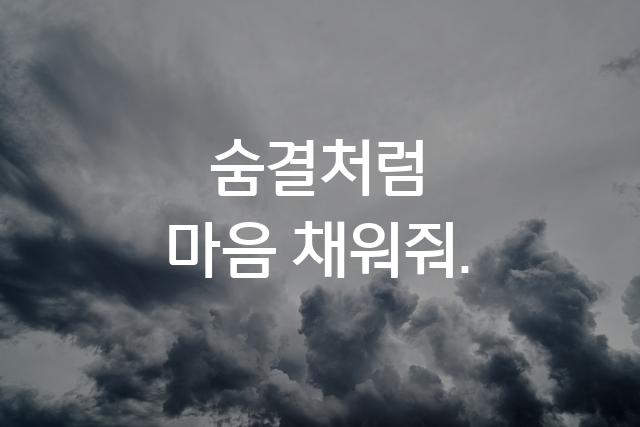
비씨카드 글꼴은 둥근 형태의 고딕체로, 부드러운 곡선이 특징입니다. 사용자에게 따뜻하고 친근한 느낌을 주며, 읽기 쉬운 디자인으로 제작되었습니다.
비씨카드 글꼴은(는)
기본 고딕, 둥근 스타일, 감성적인, 부드러움, 복실복실 계열의 생김새를 가지고 있으며
웹/앱 디자인, 보고서/문서, 출판물 제목 등에서 자주 활용되며, 효과적인 메시지 전달에 적합합니다.
이 폰트는 크리에이티브, 공공/정부, 금융/비즈니스 분야에 잘 어울리며,
신뢰감, 명확한, 전문적인 느낌을 담고 있는 것이 특징입니다.